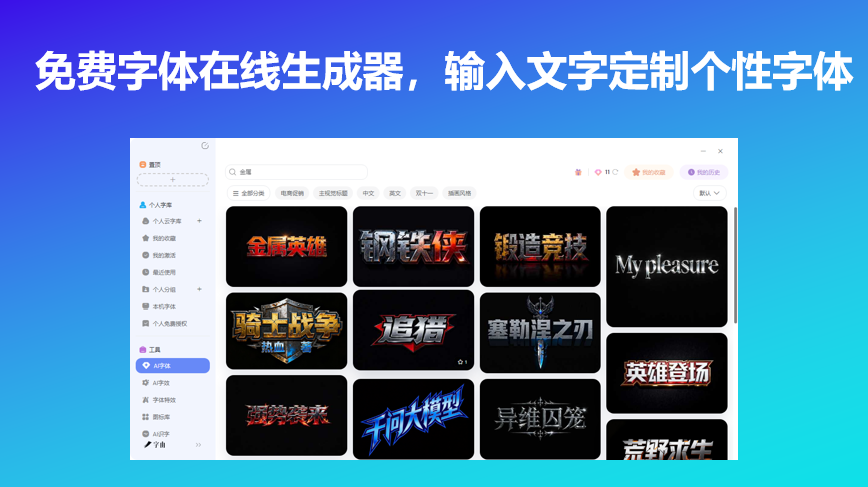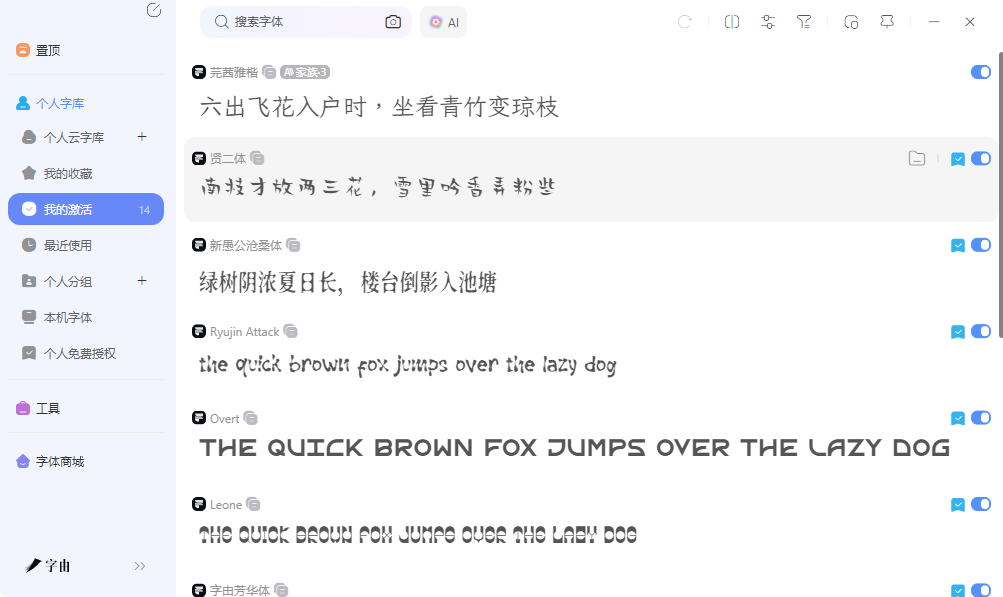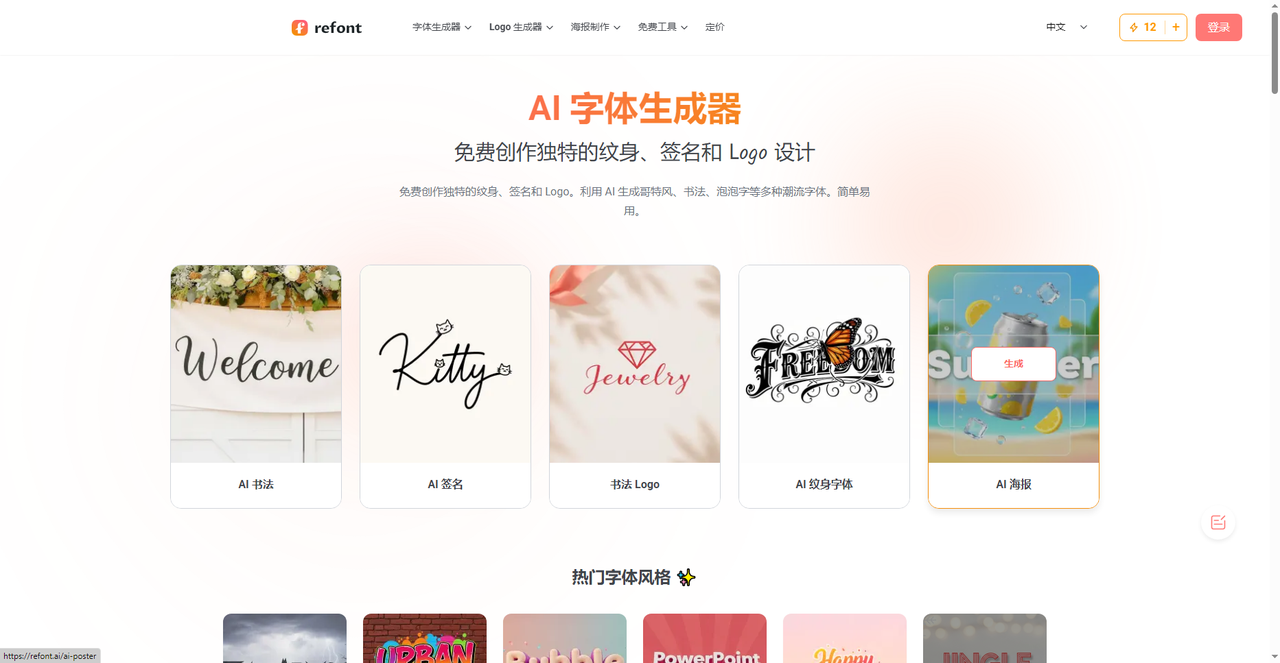
免费字体在线生成器,输入文字定制个性字体
想给自己的品牌做一款专属字体,或者把普通文字变成带特效的艺术字,不需要花大价钱请设计师。现在有不少免费在线工具,输入文字就能生成个性化字体效果,有的还能把你手写的笔迹变成可安装的字体文件。这篇文章测试了5款工具,有的提供现成模板直接套用,有的支持手写稿上传生成真迹字体,还有的可以一键复制花体字到社交媒体。操作难度和输出格式不同,只需要看这篇推荐就够了。
打开字由客户端,进入AI工具下的AI字体页面。左侧标签栏按风格分类,包括国潮风、霓虹灯、金属质感、手写书法等。每个分类下都有预制模板,模板的字体、特效、排版已经由专业设计师调校好。用户输入文案后选择一个模板,点击生成,10到15秒输出一张PNG格式图片。图片背景透明,可直接用于海报或封面。每天登录赠送6个算力点,每次生成消耗3个点。
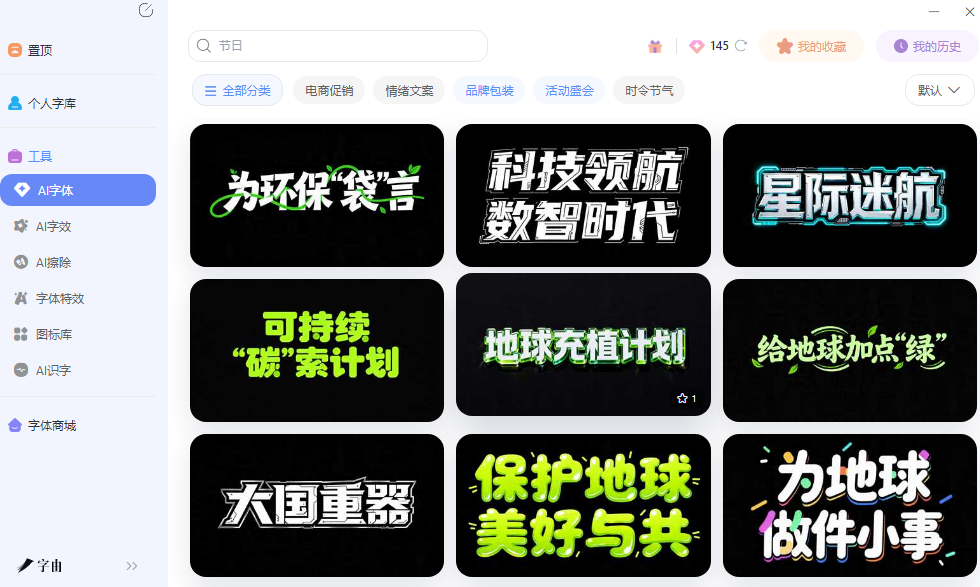
如果用户需要一款能够反复打字的现成手写体,可以使用字由的字体库激活功能。在筛选栏中勾选手写体分类,系统列出所有手写风格字体,包括演示悠然小楷、点字手写漆书、字由芳华体等。找到喜欢的字体后点击激活,该字体出现在PS、Word的字体列表中,用户打字即可呈现手写效果。激活的字体支持云字库同步,换设备登录同一账号即可使用。
2、AI字体生成器。
第二个工具是一个AI字体生成器。它的首页展示了多个应用场景:AI书法、AI签名、书法Logo、AI纹身字体、AI海报。用户可以根据需求选择对应的生成模式。该工具的核心能力是:用户输入文字,选择想要的风格(哥特风、书法、泡泡字等),AI生成对应的字体效果图。用户输入姓名,AI生成多种签名效果。用户可以选择连笔体、花体、商务签等不同风格,生成后下载图片,用于电子合同、邮件签名、简历落款。
3、Font Painter
第三个工具是Font Painter。它适合希望将自己的真实笔迹变成字体的用户。操作流程分为打印模板、手写填写、扫描上传三个步骤。
- 第一步:打印模板。用户登录Font Painter网站,找到模板下载页面。模板是PDF格式,包含所有字母(A-Z、a-z)、数字和常用标点符号的方框。每个方框内有一个灰色示例字符,用户需要在方框内手写出对应的字符。建议使用黑色凝胶笔或圆珠笔,笔迹清晰、粗细均匀。
- 第二步:手写填写。用户按照模板上的示例字符,在方框内逐个写出对应的字符。注意不要写出格,不要连笔过度,保持每个字符独立。填写完成后,使用扫描仪或手机拍照。拍照时确保光线均匀、纸张平整、没有阴影。
- 第三步:扫描上传。用户将扫描或拍照的图片上传到Font Painter网站。系统自动识别每个方框内的笔迹,切分出每个字符的轮廓,转换成矢量格式,最后打包成一个TTF字体文件。用户下载后双击安装,即可在Word、PS等软件中使用自己的笔迹字体。
手账爱好者想要一款完全属于自己的手写字体;设计师为客户定制品牌专属手写体;个人用户制作个性化签名或信件字体。
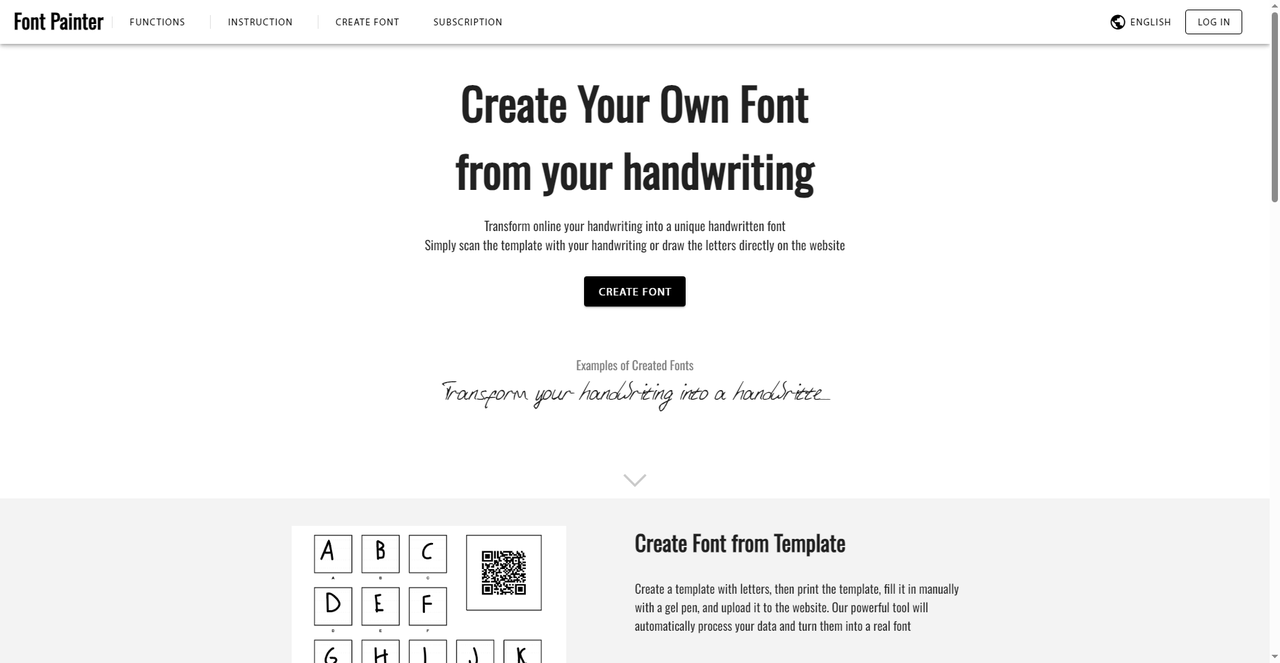
4、Font Generator
第四个网站是一个字体生成器。用户在上方输入文字,下方展示多种变形效果。
每种样式旁边有复制按钮,点击即可复制转换后的文本。该工具输出的是Unicode字符,不是图片。用户复制后可以直接粘贴到社交媒体、游戏昵称、论坛签名中,接收方不需要安装任何字体。
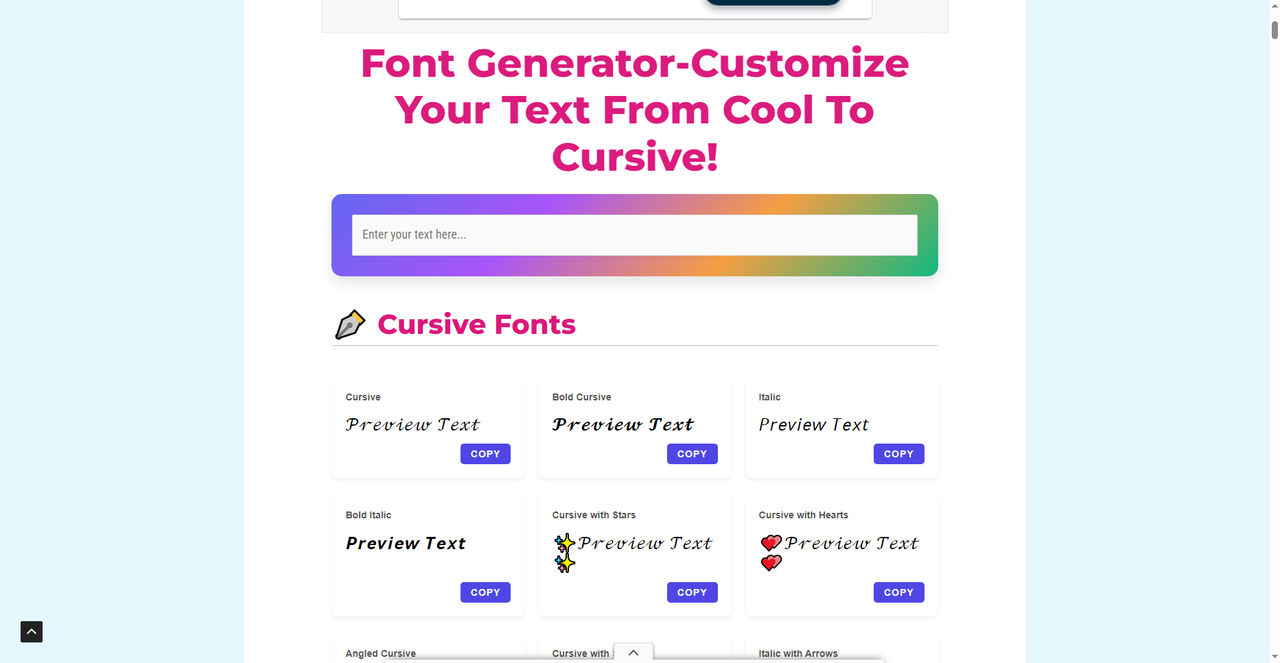
5、font generator
第五个网站是font generator。它提供了4700多种字体样式和100多种文字效果,用户在上方输入文字,系统立即展示所有可用的字体样式预览。样式按类别分组,包括手写体、草书、优雅体、涂鸦体、哥特体、古风体、恐怖体、迪士尼风格、漫画体等。每种样式下方有复制按钮,点击即可复制转换后的文本。用户还可以将文字转换为图片下载(Text to image fonts功能),适合需要一次性输出标题图的场景。
4700多种样式意味着用户几乎可以找到任何风格的英文字体变体。从传统的衬线体、无衬线体,到装饰性的花体、气泡体,再到实验性的故障体、像素体,应有尽有。每种样式都经过Unicode字符映射预处理,确保复制后能正常显示。
社交媒体文案需要频繁更换不同风格的字体;设计灵感参考,快速预览某一种效果是否适合自己的项目;教学演示,展示同一段文字在不同字体下的表现差异。
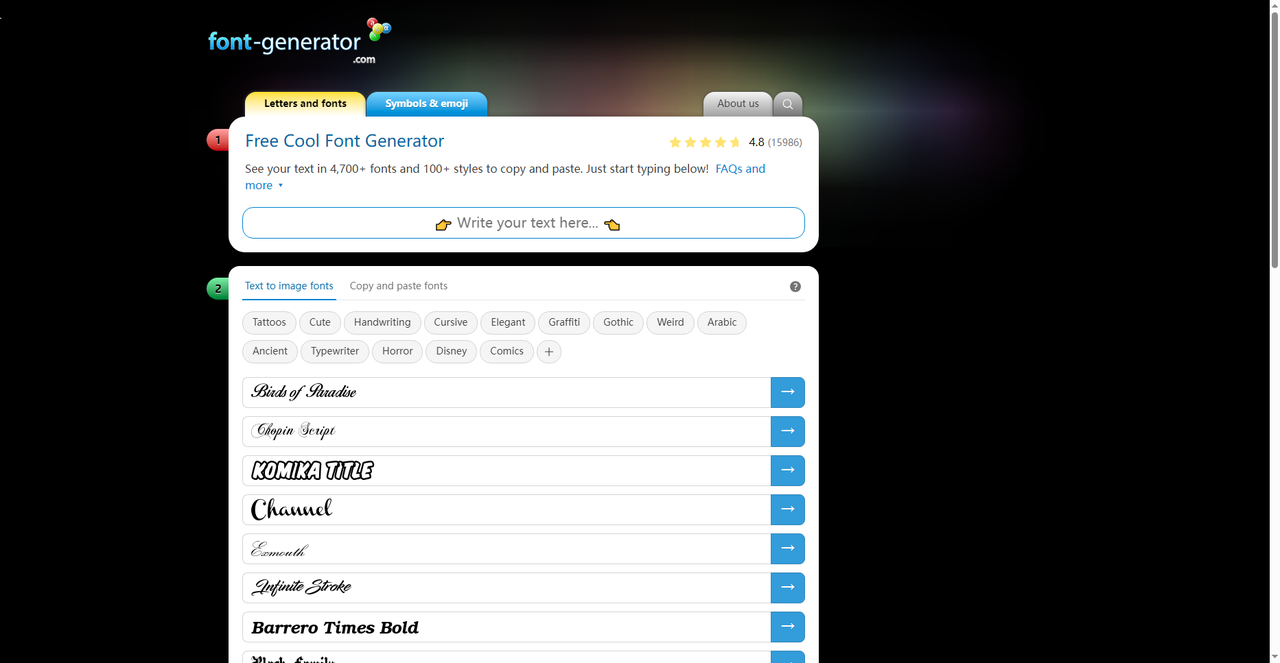
字由的预制模板直接替换文字就能出图,每天免费额度够用。AI字体生成器专攻哥特风、书法体,适合纹身和签名场景。Font Painter把手写稿变成可安装字体,真实笔迹无法复制。Font Generator提供诅咒体及爱心、星星等装饰变体,一键复制到社交平台。font generator有四千多种样式,花体、哥特、涂鸦随便挑。输入文字,选一个工具,几分钟拿到结果。不需要设计基础,也不用装软件。哪个顺手用哪个,不用纠结。